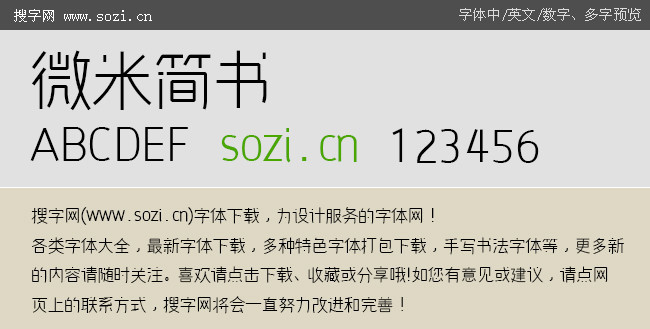
微米簡書
搜字網(wǎng)給大家提供一款微米簡書中文字體下載,微米簡書字體是微米字庫中一款非常簡單可愛的藝術(shù)字體,字體筆觸粗細(xì)適中,稚嫩可愛,具有很好的視覺感,適合應(yīng)用于藝術(shù)設(shè)計、平面宣傳設(shè)計、網(wǎng)頁設(shè)計,書法字帖等領(lǐng)域。